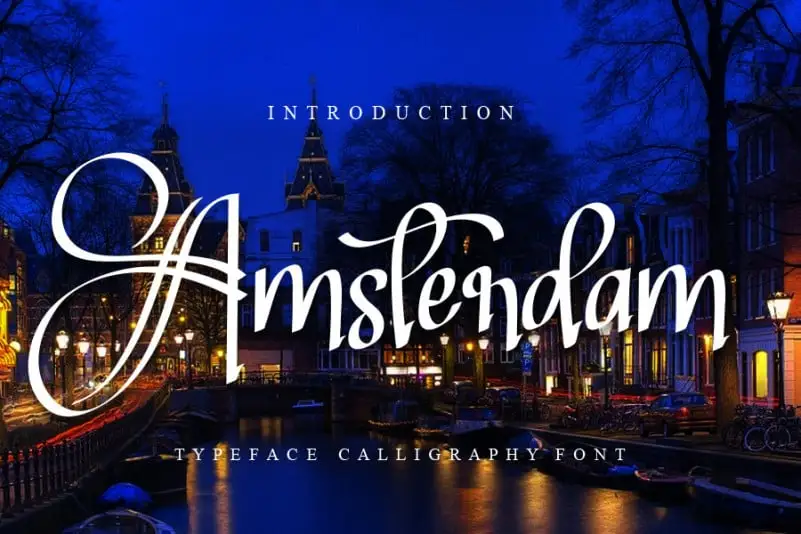
Na categoria de fonts para escrita por ela, a Amsterdam Font oferece uma experiência única e diversificada, perfeitamente adaptada para artistas digitais e criativos buscando expressar suas ideias de formas diferentes. Criados pelo designer creativeletter, esses produtos chamam atenção com sua capacidade de transformar qualquer texto em um verdadeiro trabalho de arte, seja através de códigos épicos, desenhos exuberantes ou escrita clássica. Essas fontes foram projetadas para proporcionar aos usuários uma experiência extraordinária e personalizada, perfeitamente adaptada às necessidades individuais dos criativos brasileiros. Seja você um designer gráfico, editor de imagem ou simplesmente alguém que ama a forma como o texto pode ser moldado em formas artísticas, Amsterdam Font oferece a oportunidade para expressar suas ideias de maneira única e inspiradora.